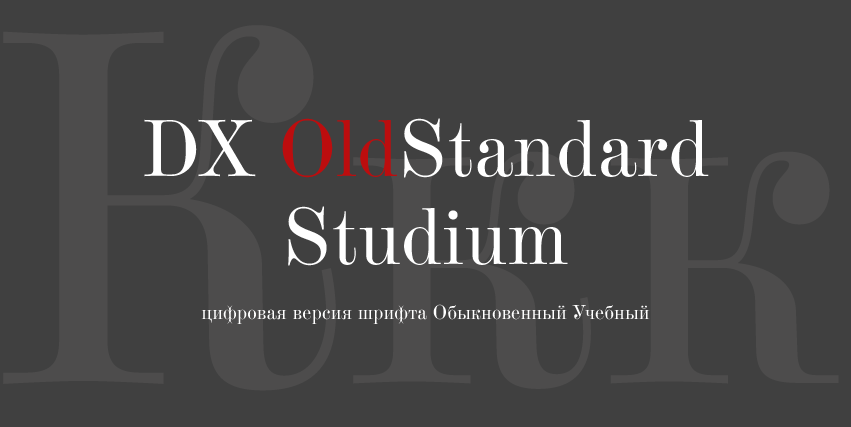
Шрифт Обыкновенный учебный/DXOldStandardStudium.
Выпущен шрифт DXOldStandard Studium - цифровая версия металлического шрифта "Гарнитура № 3 Учебная" по ОСТ 1337 или "Гарнитура № 11 Обыкновенный" по каталогам Словолитни О.Лемана, использовавшийся для набора учебников, букварей и пособий для начальных школ в начале ХХ века.